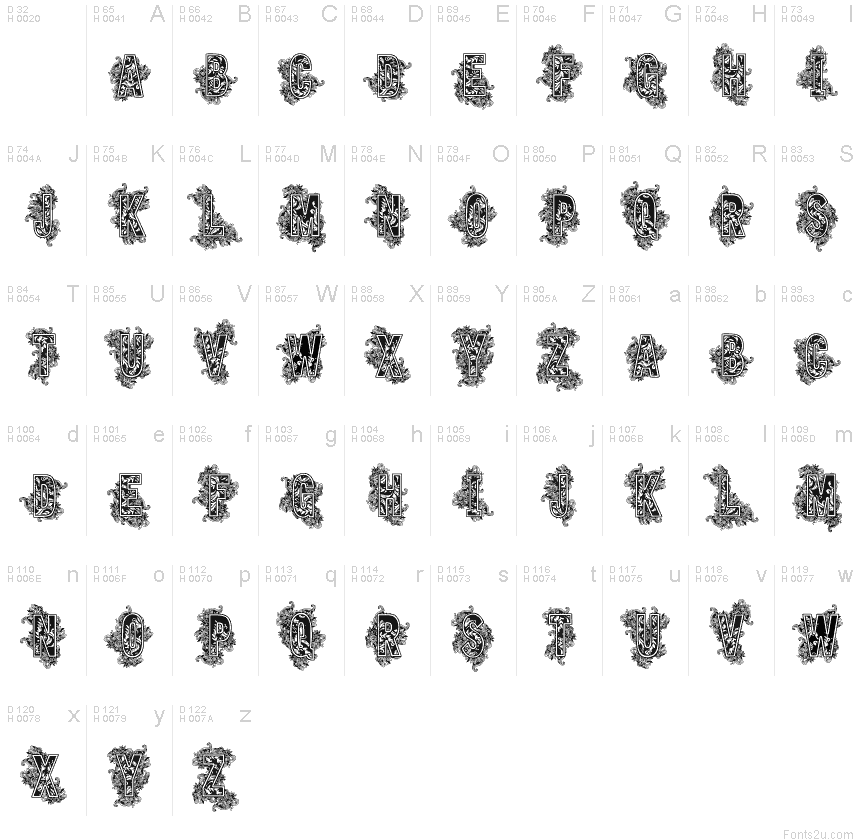
VTKS Beauty od Douglasa Vitkauskasa to darmowy botaniczny font display, składający się wyłącznie z wielkich liter, utrzymany w klimacie wiktoriańskich tatuaży typu flash. Litery są wypełnione kunsztownymi, wijącymi się liśćmi i płatkami, a wyraziste zewnętrzne kontury sprawiają, że ozdobne detale nie zlewają się w drobny wzorek.
Font świetnie sprawdzi się w brandingu perfum, nagłówkach zaproszeń, opakowaniach kosmetyków, tytułach plakatów czy na okładkach, gdzie dekoracyjne wypełnienie może grać główną rolę. Jako darmowe pismo, jest także doskonałym wyborem do monogramów i krótkich napisów, ponieważ gęste, kwiatowe wnętrza liter potrzebują oddechu, by przyciągnąć wzrok, zamiast być rozciąganymi w długich tekstach.